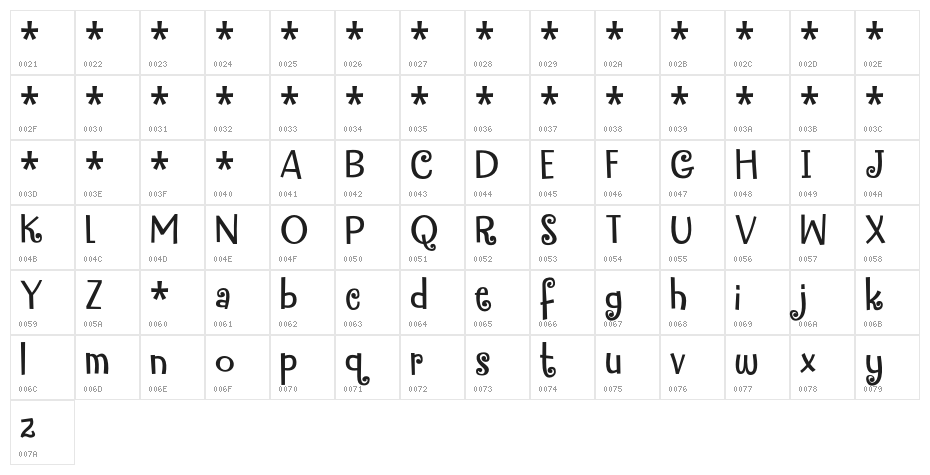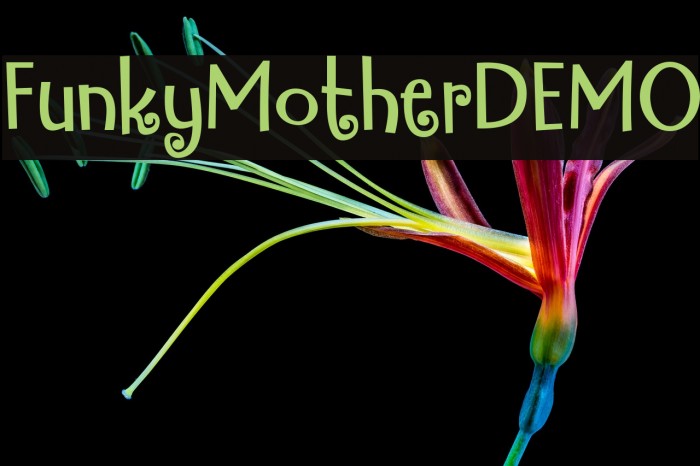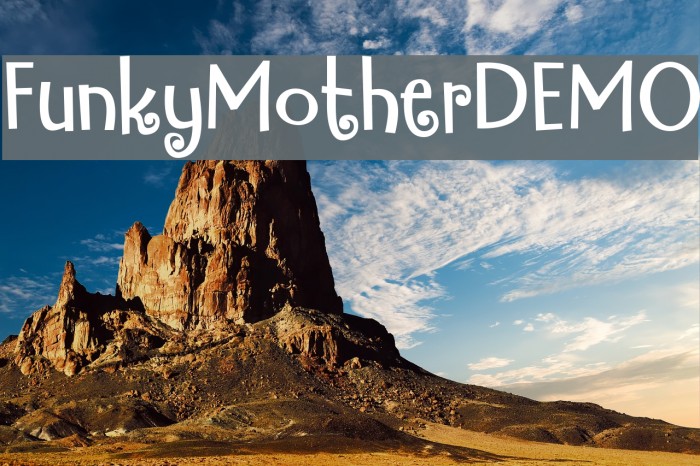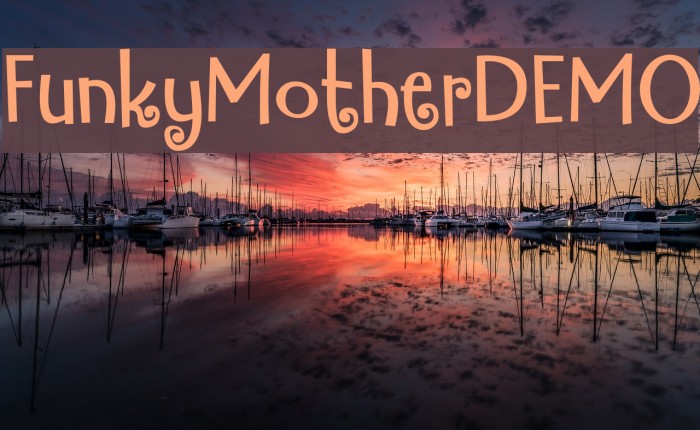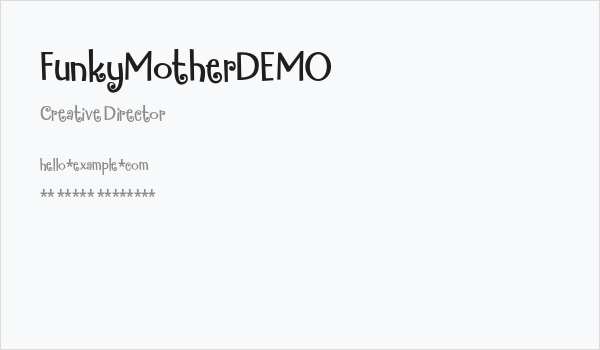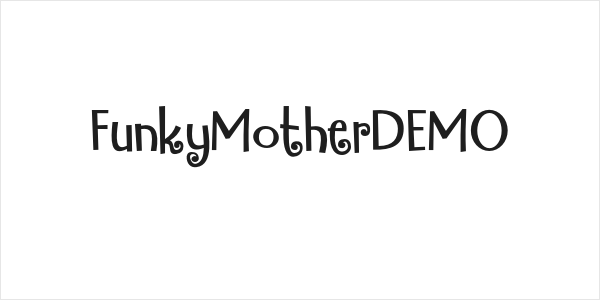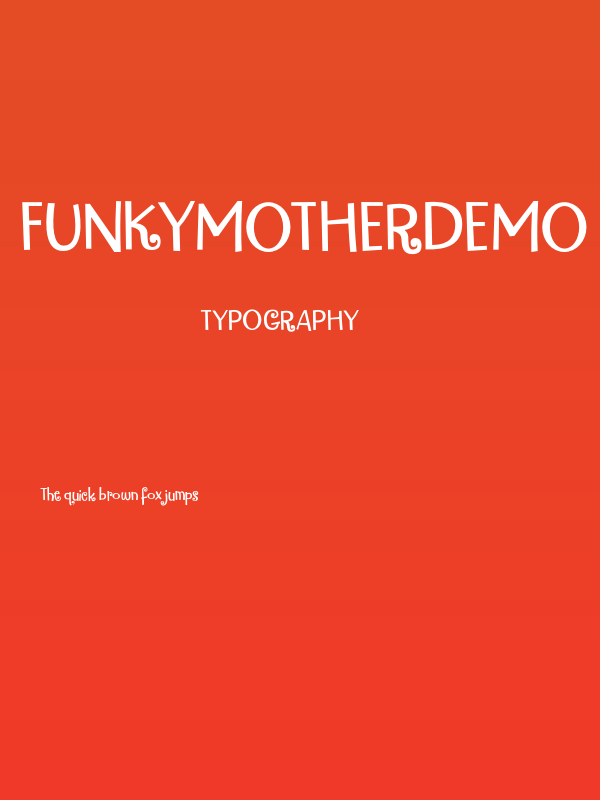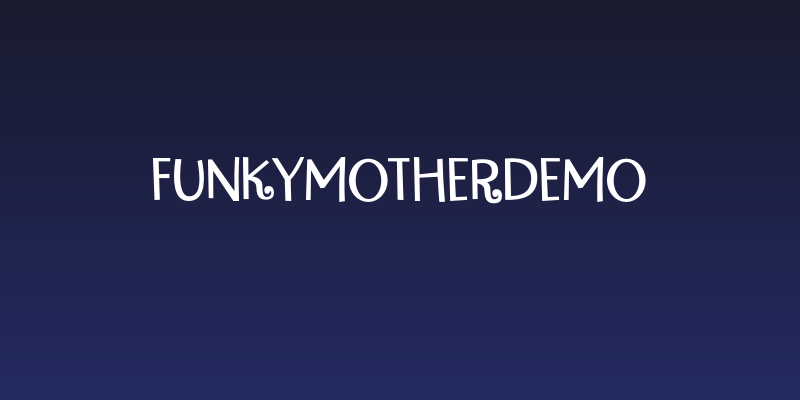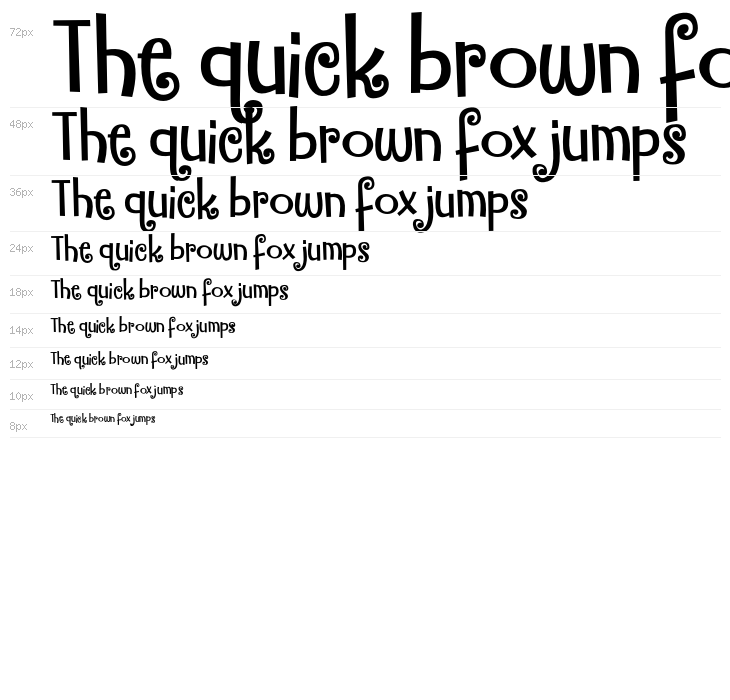
FunkyMotherDEMO Font
✎ Curly
| Categorie | Curly |
| Stile generale | Playful, Whimsical, Decorative |
| Progetti proposti | Ideal for children's books, party invitations, playful branding, and creative posters. |